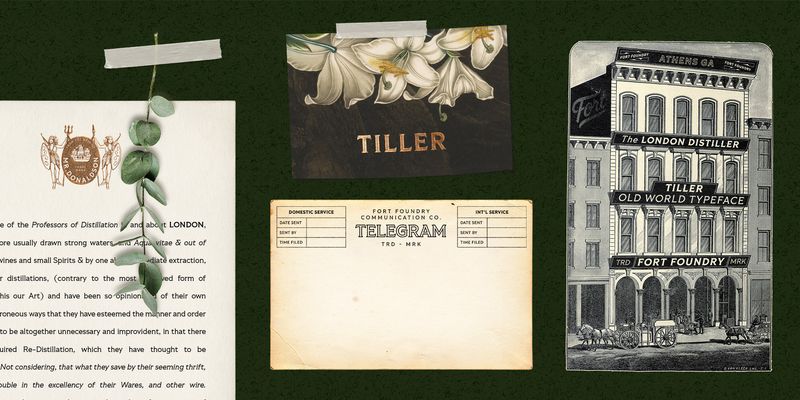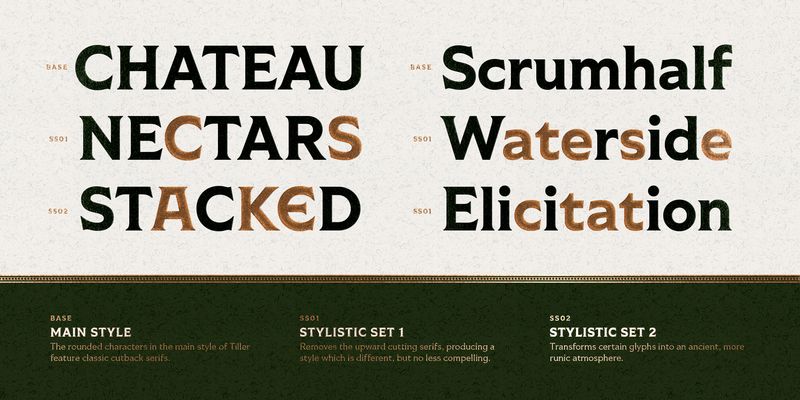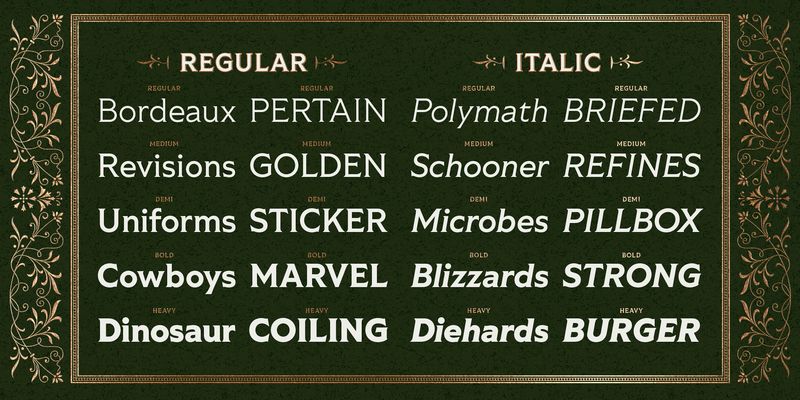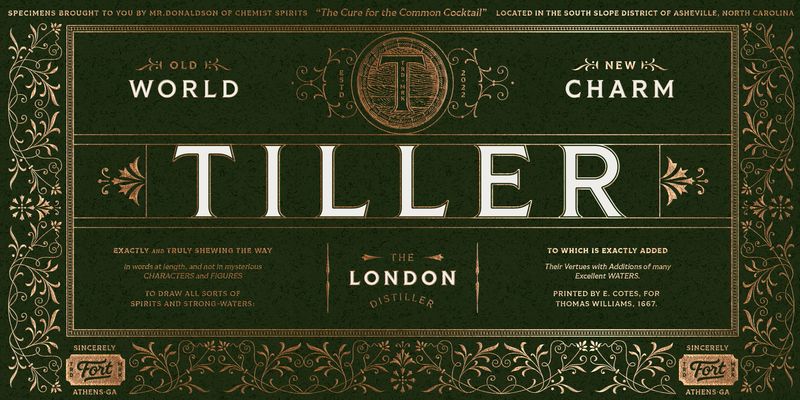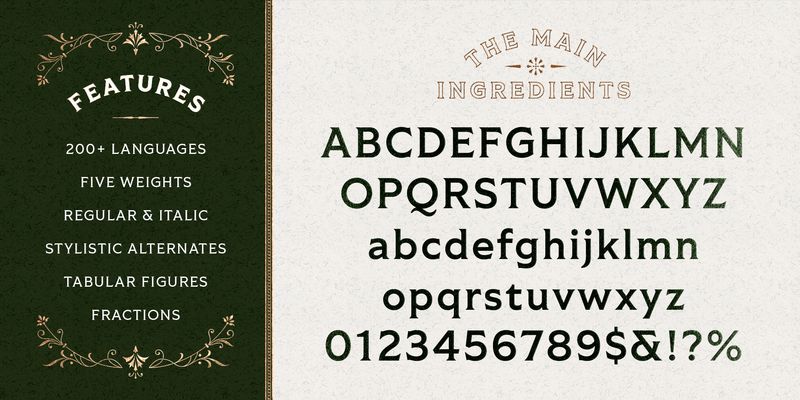
Inspirada en formas geométricas, la tipografía románica y un eterno amor por lo efímero del siglo XIX, Tiller equilibra sus formas con ostentosidad y funcionalidad. Alejada de las tendencias más recargadas de Shackleton, esta familia apuesta por un estilo más industrial con cinco grosores que van desde Regular a Heavy con estilos latino y de cursiva. Tiller admite más de 200 idiomas y cuenta con multitud de características tipográficas, como alternativas estilísticas, puntuación que distingue entre mayúsculas y minúsculas y mucho más.